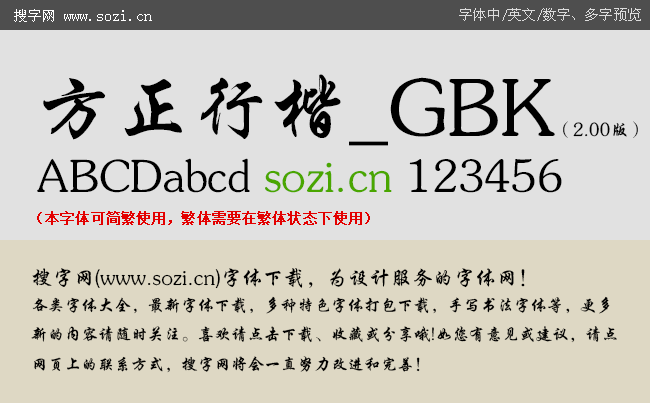
方正行楷_GBK
搜字網(wǎng)提供一款方正行楷_GBK中文字體下載,方正行楷_GBK是一款非常大方的行楷字體,方正行楷體瀟灑大方,整體效果十分出色,GBK碼包含字體更全,適合應(yīng)用于廣告設(shè)計(jì)、名片設(shè)計(jì)、包裝印刷、兒童產(chǎn)品設(shè)計(jì)等應(yīng)用。
• 風(fēng)格類別: 行楷